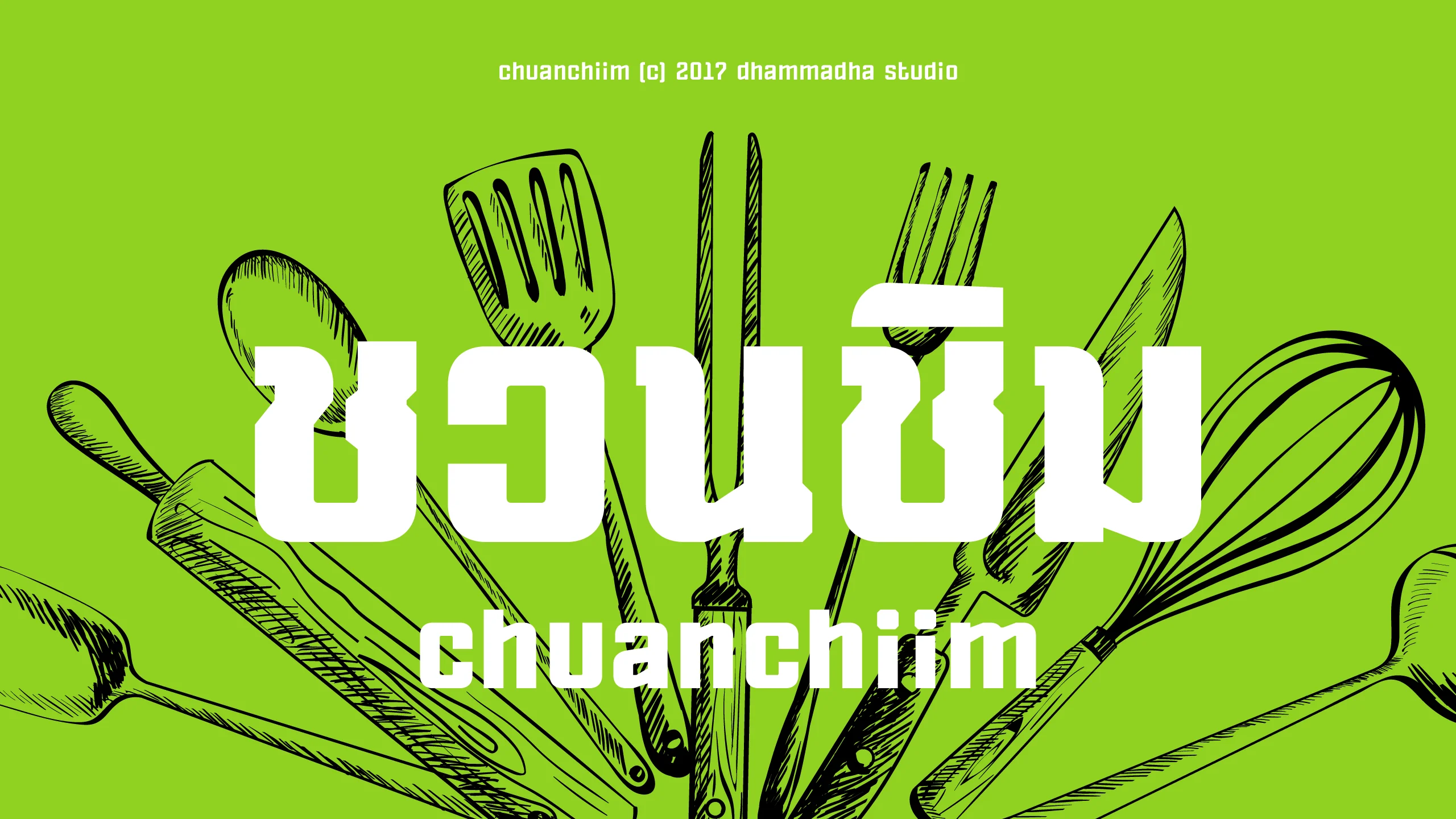
chuanchiim
ชุดอักษรที่ตั้งใจถ่ายทอดรูปลักษณ์อันคุ้นตาในความทรงจำวัยเด็ก โดยได้รับแรงบันดาลใจมาจากเสน่ห์ของป้ายร้านอาหารในยุคอดีตอย่าง 'เชลล์ชวนชิม' ซึ่งเป็นภาพจำแรกที่ผูกพันกับชีวิตในร้านอาหารของครอบครัว เราจึงหยิบยกบุคลิกอันเป็นเอกลักษณ์ของตัวอักษรบนป้ายดั้งเดิมมาปัดฝุ่นใหม่ เพื่อให้กลิ่นอายความคลาสสิกเหล่านั้นกลับมาโลดแล่นอีกครั้งในงานออกแบบยุคปัจจุบัน สะท้อนภาพลักษณ์ที่เต็มไปด้วยเรื่องราว ความเป็นกันเอง และรอยยิ้มของวันวาน แม้ตัวอักษรจะให้ความรู้สึกที่ย้อนยุค (Retro) แต่เราได้ปรับปรุงสัดส่วนและการจัดวางให้มีความร่วมสมัยและรองรับการใช้งานที่หลากหลายมากขึ้น เหมาะอย่างยิ่งสำหรับงานออกแบบแบรนด์อาหารและเครื่องดื่ม ร้านคาเฟ่สไตล์วินเทจ หรือสื่อโฆษณาที่ต้องการสร้างบรรยากาศอันอบอุ่นและเป็นมิตร "ชวนชิม | chuanchiim" จะช่วยเปลี่ยนงานดีไซน์ของคุณให้ดูมีรสชาติและเปี่ยมด้วยเสน่ห์ที่ชวนให้ผู้คนหวนคิดถึงรสชาติแห่งความสุขในอดีต